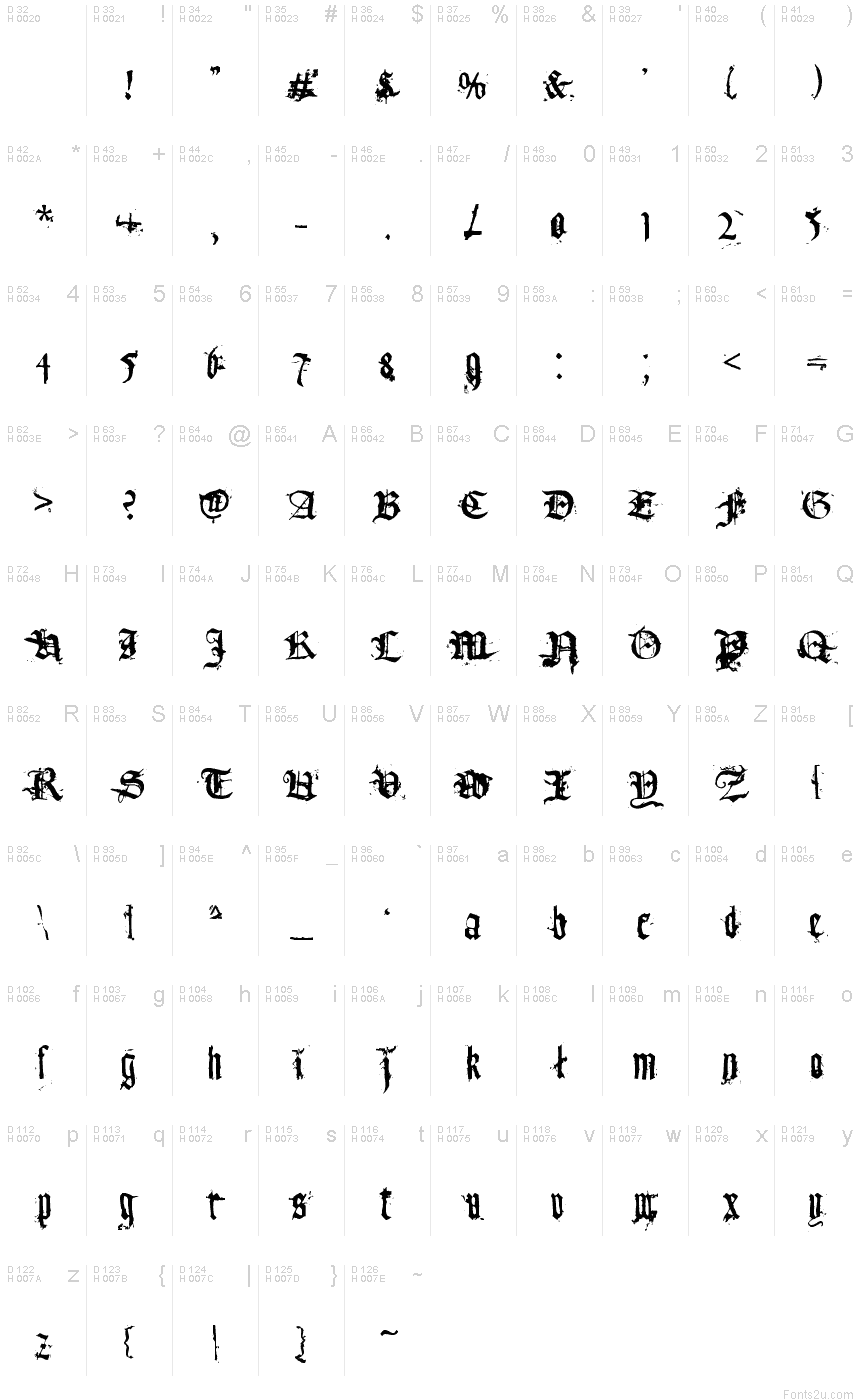
Tfu Tfu von Meir Sadan ist eine kostenlose, distressed Blackletter-Display-Schrift mit einem rauen, abgenutzten mittelalterlichen Charakter. Die Buchstaben lehnen sich an alte gotische Formen an, aber durch die abgeplatzten Kanten und splittrigen Brüche wirkt sie keineswegs zeremoniell – sie sieht grob, fleckig und ein wenig konfrontierend aus.
Das macht diese kostenlose Schrift zur idealen Wahl für Poster-Überschriften, Zine-Cover, Band-Logos, Titelkarten und Verpackungen, die eine düstere, historische Stimmung erzeugen sollen, ohne dabei zu ordentlich oder ornamental zu wirken. Sie funktioniert am besten dort, wo ein paar Worte die Textur tragen können, insbesondere bei kurzen Schlagzeilen oder monogrammartigen Initialen, da die zerschundenen Blackletter-Formen bereits so viel Aussagekraft besitzen.
My kitty can make fonts. One day I was hanging around with my lovely kitty-cat, browsing different types of fonts. My kitty surprisingly started to stare at each typeface, examining its typographical correctness and structure, the serifs and the stroke angle. Suddenly, she meowed. It wasn't the regular kind of meow - it was her special meow. The meow she uses to greet people she likes... At that moment, it just hit my mind - my kitty happens to like Goudy's typeface.
Goudy is that font on the cover of The New York Times... The one that says "The New York Times". Yeah. Anyways... My kitty seemed to get all giddy and stuff, so I made a printout of it and let my kitty play with it.
In a very extreme measure of carefulness, she started toodling around with the font - scrach here, scratch there - wrinkle here, wrinkle there. She started to get bored from this routine quite fastly, so I took the poor piece of paper and rolled it to the shape of the ball. You should've seen the look of graditude on her face when she found out she could now both play and make a font at the same time!
To make a long story short, I eventually took the wad of material previously known as a piece of paper and scanned it into a font. And now you can have it. So there.